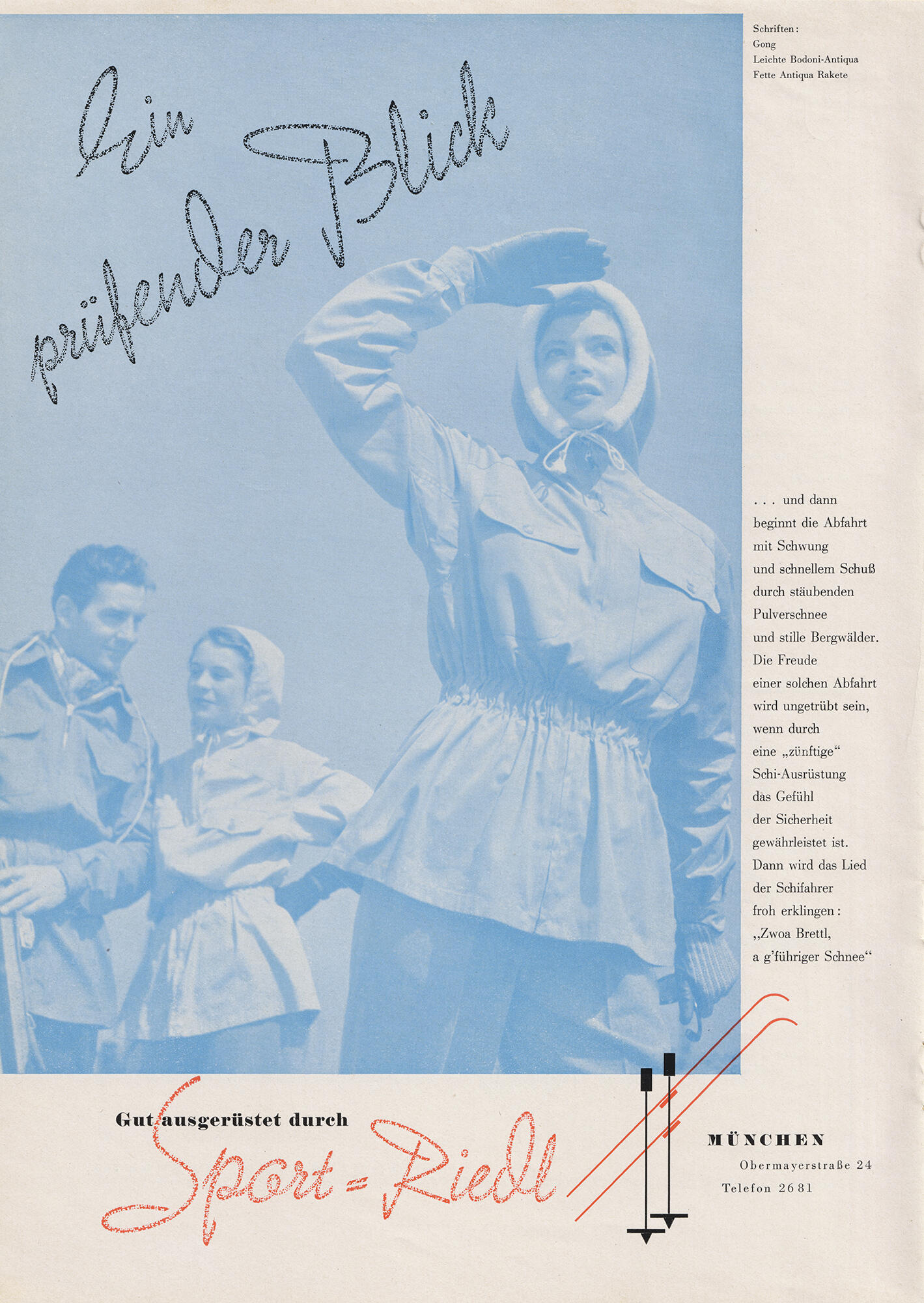
Font-Wiki: Kreideschrift Gong
Die (Kreideschrift) Gong von Carlos Winkow erschien 1945 bei der Norddeutschen Schriftgießerei, die später Johannes Wagner heißt. Die auffällige Kreide-Effekt erstreckt sich gleichmäßig über alle Bleisatz-Größen, wächst also in der Größe nicht mit. Auch Linien und Unterstreichungen mit dem gleichen Effekt waren erhältlich.
Eine Digitalisierung als Bad Gong gibt es von Peter Wiegel.